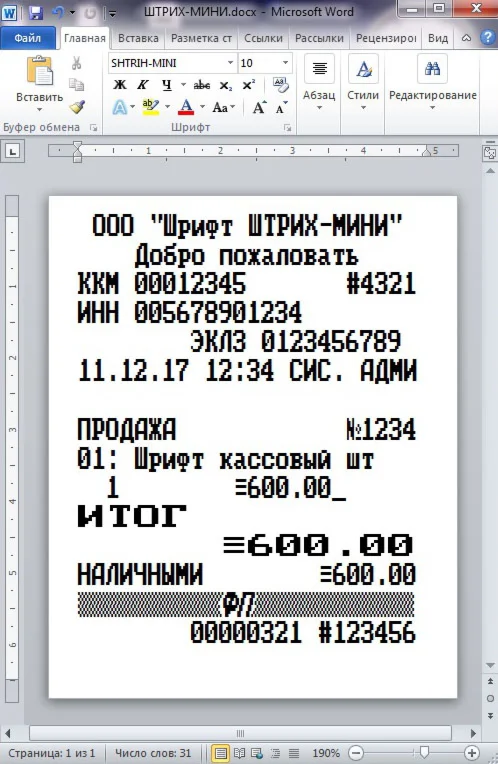
Магазин » Шрифт ККМ ШТРИХ-МИНИ, ЭЛВЕС-МИНИ(ttf)
Шрифт кассовых аппаратов ШТРИХ-МИНИ и ЭЛВЕС-МИНИ в формате TTF (русские и английские буквы) для использования в программе Microsoft Word. В архиве находятся стандартный и жирный шрифты в формате TTF и шаблон чека. Вам остается только установить шрифты в систему (обычно C:\WINDOWS\Fonts), открыть шаблон и начать редактирование. Печатать чеки предпочтительно на термопринтере, на кассовой термоленте. Хотя можно печатать и на струйнике и лазерном, с возможностью вывода на факсовую бумагу. Лучшее качество, естественно, при печати на термопринтерах.